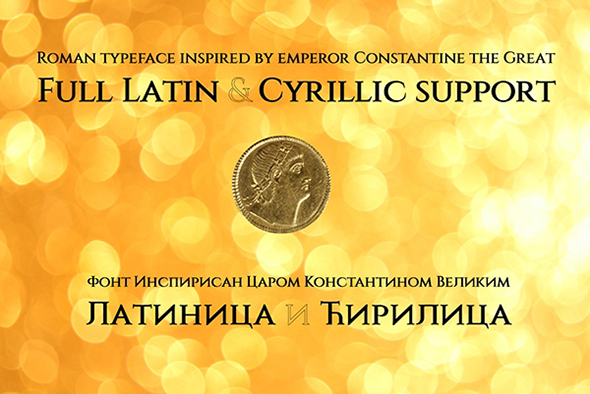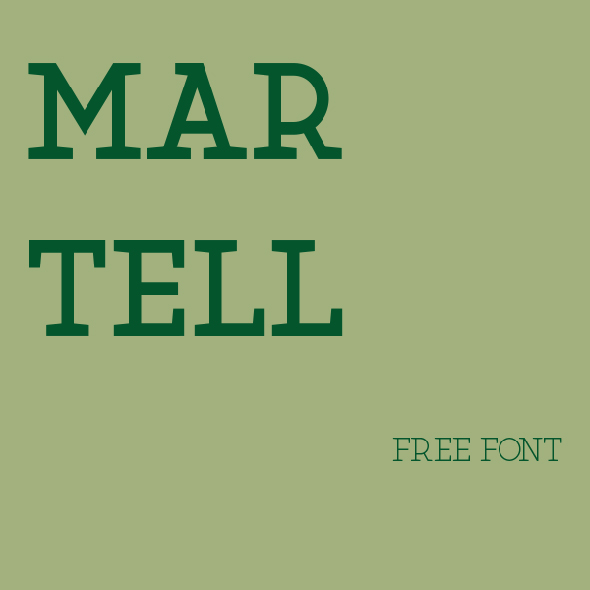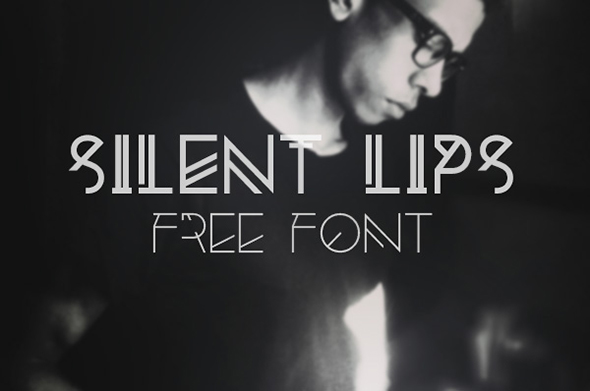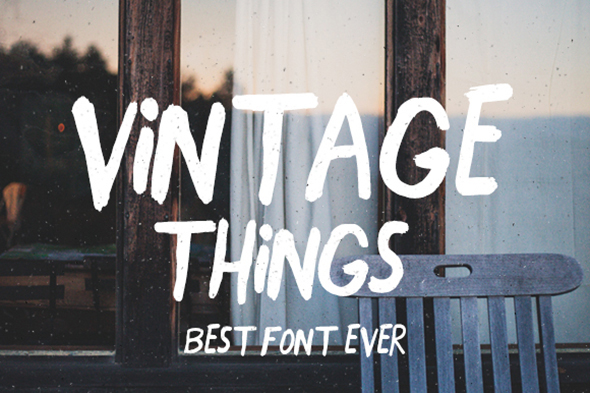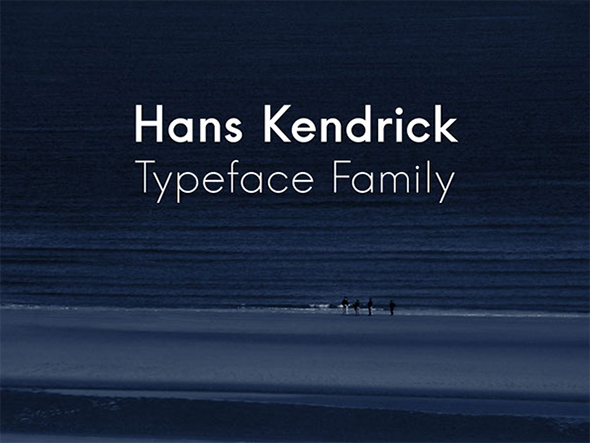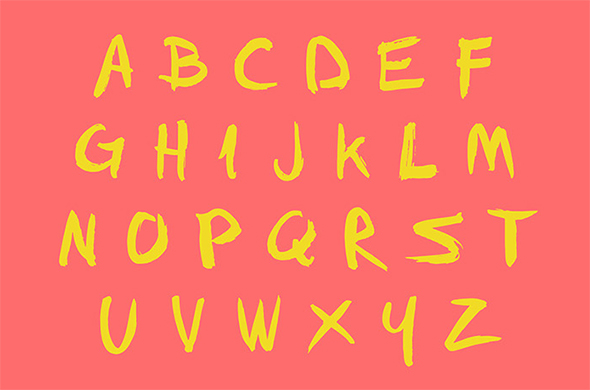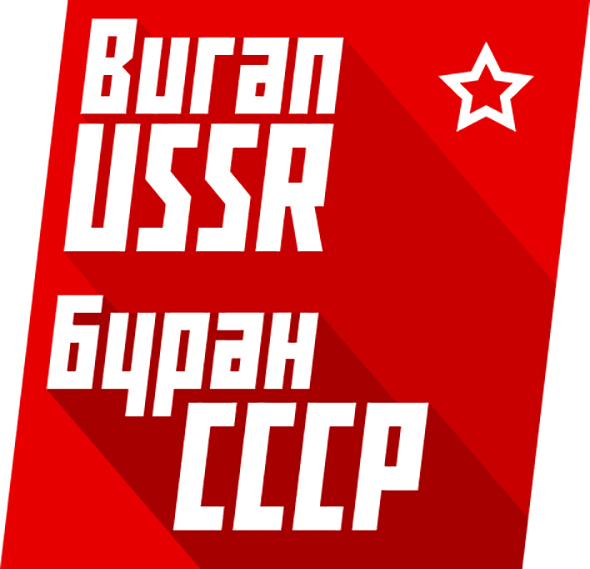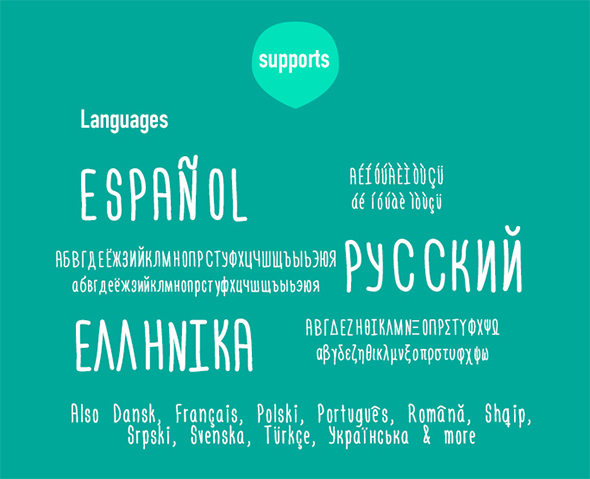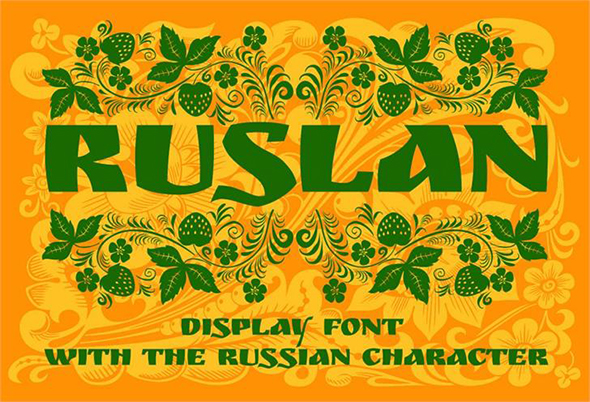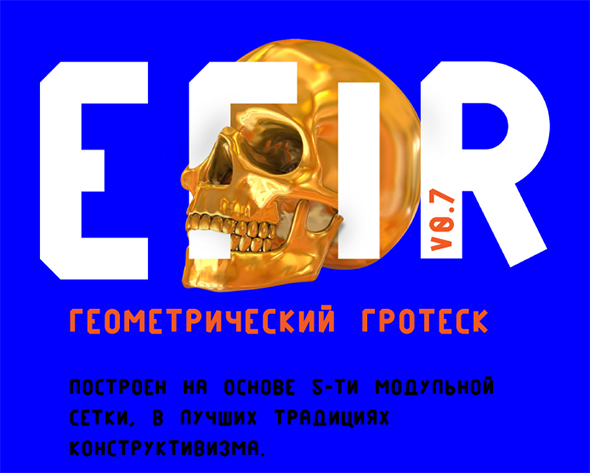
Бесплатные латинские и кириллические шрифты
Если вам кажется, что библиотека ваших шрифтов бедновата, мы можем вам помочь. Спешим поделиться традиционной подборкой шрифтов на все случаи жизни. В первой части публикации представлены шрифты с кириллической версией, во второй же — лишь латиница. Вы найдете начертания в самых разных стилях, которые можно использовать для заголовков, типографических работ, логотипов или же обычного текста. Выбирайте и используйте!
Кириллица
Constantine
Buran USSR
L'Engineer Font
Ruslan Display font
EFIR
Arkiv
Monitorca
Ahellya
Tenor Sans
Латиница
Martell
Bushcraft
JAAPOKKI
Silent Lips
Close Font Family
Passion
AVENTURA
Hanken Round
Hans Kendrick
FFAD Matro
Fox & Cat Typeface